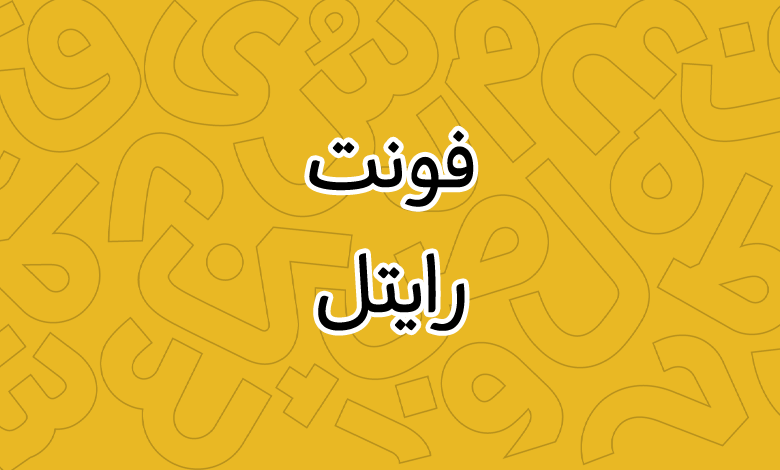
فونت رایتل (Rightel)
فونت رایتل (به انگلیسی: Rightel) یکی دیگر از قلمهای طراحی شده برای استفاده در متون بلند بهویژه برای مطبوعات و نامهنگاری اداری است که میتوانید از آن استفاده کنید. این فونت با فرمتهای استاندارد در دسترس است که در ادامه با دانلود فونت رایتل با شما همراه هستیم.
طراح فونت رایتل حسین زاهدی است که پیش از این مهمترین اثر وی، یعنی فونت رایگان نستعلیق بررسی کردهایم. این فونت که به سبک خط نسخ طراحی شده، از نظر چینش حروف جزو فونتهای درشت محسوب میشود که خوانایی بسیار بالا و خوبی دارد.
فونت فارسی رایتل محدود به این زبان نیست و از سایر زبانهای خاورمیانهای بهویژه زبان عربی پشتیبانی میکند. تمامی گلیفهای زبان فارسی و عربی به شکل استاندارد در این فونت پیادهسازی شدهاند. حروف متفاوت عربی «ک، ی، ه، ؤ، ئ» دارای گلیف اختصاصی خود هستند که برای استفادههای دو زبانه نیاز شما را بهطور کامل برطرف میکند.
دیگر زبان پشتیبانی شده در این فونت انگلیسی است که برای حروف لاتین نیز این فونت گلیفهای خاص خود را دارد. البته از طراحی اختصاصی بهره نمیبرد و از فونتهای آزاد دیگر برای آن استفاده شده است.
ظاهر حروف فونت رایتل TTF به شکلی طراحی شده که درشت بهنظر میرسند. از سوی دیگر ظاهر حروف که دارای خطوط عمودی هستند به مقدار کمی به سمت چپ زاویه داده شده که آن را کمی ایتالیک کرده است. دندانهها دارای فاصله مناسبی از یکدیگر هستند و گردی برخی حروف نیز کمی فشرده و به خط کرسی نزدیکتر شده تا فونت کمی ساختار فشرده بهخود بگیرد.
تنها ایراد جزئی فونت رایتل، عدم پشتیبانی استاندارد اعداد است. برای زبان فارسی از همان نسخه اعداد عربی «۰۴۵۶» استفاده شده که انتظار میرود در نسخههای بعدی شاهد افزودن اعداد فارسی «۰۴۵۶» در این فونت باشیم.
این فونت برای استفاده در متون بلند گزینهای عالی محسوب میشود که میتوانید در حوزه چاپ برای متون روزنامه و مجلات یا کتاب از آن استفاده کنید. دیگر کاربردهای این فونت برای بیلبوردهای اطلاعرسانی یا فضای وب است.